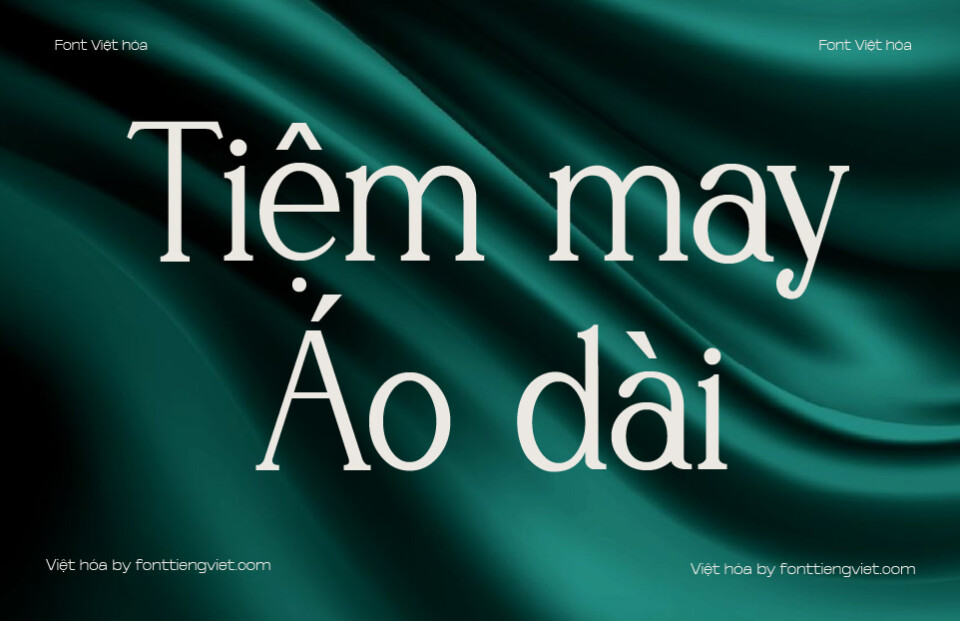
Font Việt hóa 1FTV VIP Weigeland
Giới thiệu về Font Việt hóa 1FTV VIP Weigeland
Trong thế giới thiết kế đồ họa hiện đại, việc lựa chọn một phông chữ phù hợp không chỉ giúp truyền tải nội dung mà còn thể hiện phong cách và đẳng cấp của tác phẩm. Font Việt hóa 1FTV VIP Weigeland là một trong những lựa chọn hàng đầu dành cho các nhà thiết kế đang tìm kiếm sự hòa quyện giữa nét cổ điển và hơi thở đương đại. Đây là bộ phông chữ được tinh chỉnh kỹ lưỡng về dấu tiếng Việt, đảm bảo tính thẩm mỹ cao và sự mượt mà trong từng nét chữ. Khi bạn sử dụng Font Miễn Phí để sáng tạo, sự xuất hiện của Weigeland sẽ mang đến một làn gió mới đầy ấn tượng cho các dự án từ học đường đến chuyên nghiệp.
Đặc điểm nổi bật của Font Việt hóa 1FTV VIP Weigeland
Thiết kế thanh lịch và đa dụng
Bộ Font Việt hóa 1FTV VIP Weigeland sở hữu những đường nét mảnh mai nhưng vô cùng chắc chắn. Cấu trúc của chữ được thiết kế theo phong cách Serif tối giản, giúp người xem dễ dàng đọc nội dung mà không gây mỏi mắt. Điều này đặc biệt quan trọng khi áp dụng vào các tài liệu giảng dạy hoặc bài thuyết trình của học sinh. Sự cân bằng giữa các khoảng cách chữ giúp bộ font này trở nên linh hoạt, phù hợp cho cả tiêu đề lớn lẫn các đoạn văn bản ngắn cần sự trang trọng.
Khả năng hiển thị tiếng Việt hoàn hảo
Một trong những điểm cộng lớn nhất của Font Việt hóa 1FTV VIP Weigeland chính là hệ thống dấu câu được tối ưu hóa. Các dấu thanh trong tiếng Việt thường dễ bị lỗi đè chữ hoặc lệch vị trí ở các bản font quốc tế, nhưng với phiên bản 1FTV VIP này, mọi ký tự đều hiển thị chuẩn xác và đẹp mắt. Điều này giúp các bạn sinh viên và thầy cô giáo hoàn toàn yên tâm khi thiết kế bìa tiểu luận, báo tường hay các ấn phẩm truyền thông nội bộ của nhà trường.
Ứng dụng thực tế của Font Việt hóa 1FTV VIP Weigeland trong đời sống
Với vẻ đẹp tinh tế, Font Việt hóa 1FTV VIP Weigeland thường được ưu tiên sử dụng trong các mẫu thiệp mời, bao bì sản phẩm cao cấp và đặc biệt là trong thiết kế thương hiệu cá nhân. Trong môi trường giáo dục, bộ font này có thể dùng để trình bày các chứng chỉ khen thưởng, tạo nên sự trang trọng và ghi nhận xứng đáng cho những nỗ lực của cá nhân. Ngoài ra, các bạn trẻ yêu thích sáng tạo nội dung trên mạng xã hội cũng có thể tận dụng Weigeland để làm nổi bật hình ảnh của mình thông qua các trích dẫn ý nghĩa hoặc tiêu đề video clip sinh động.